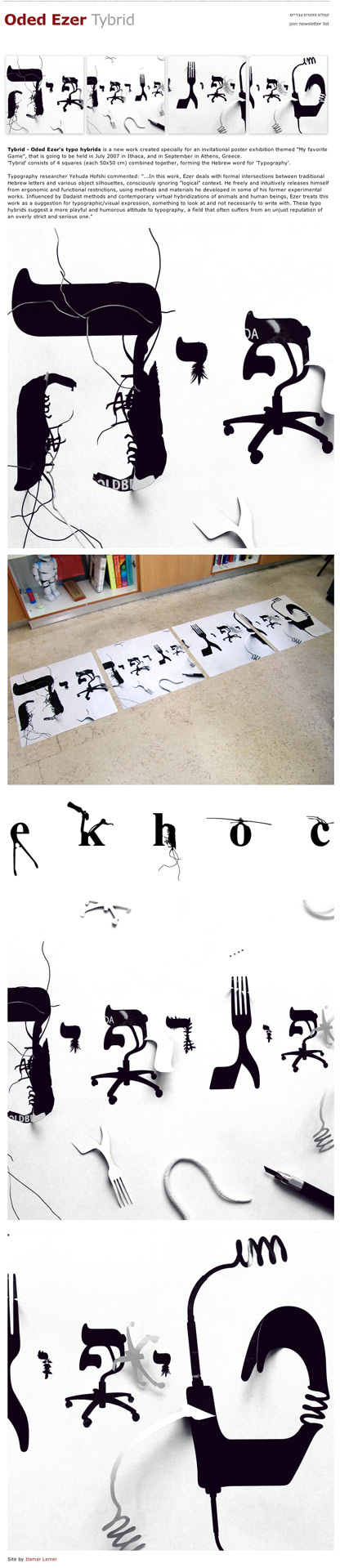
Tybrid par Oded Ezer | Typographie et formes espiègles
Tybrid – les typos hybrides d’Oded Ezer est un nouveau travail créé particulièrement pour une exposition d’invitation d’affiche ayant pour thème «mon jeu préféré», elle va se tenir en juillet 2007 à Ithaca, et en septembre à Athènes, Grèce.
«Tybrid» se compose de 4 pièces (chaque 50×50 centimètre) combinées ensemble, formant le mot hébreu pour la « typographie ».
C’est ainsi que le chercheur en typographie Yehuda Hofshi commente les travaux de Oded Ezer :
« … Dans ce travail, Ezer traite les intersections formelles entre les lettres hébreuses traditionnelles et les diverses silhouettes d’objet, ignorant consciemment tout contexte «logique». Il se libère librement et intuitivement des restrictions ergonomiques et fonctionnelles, en utilisant des méthodes et des matériaux qu’il a développé dans certains de ses anciens travaux expérimentaux. Influencé par des méthodes de Dadaist et des hybridations virtuelles contemporaines sur des animaux et êtres humains, Ezer traite ce travail comme une suggestion pour l’expression typographique/visuelle. Quelque chose regarder et écrire pas nécessairement avec. Ces typos hybrides suggèrent une attitude plus espiègle et pleine d’humour envers la typographie, un champ qui souffre souvent d’une réputation injuste de excessivement stricte et sérieuse. » (Traduction Google amélioré :-)